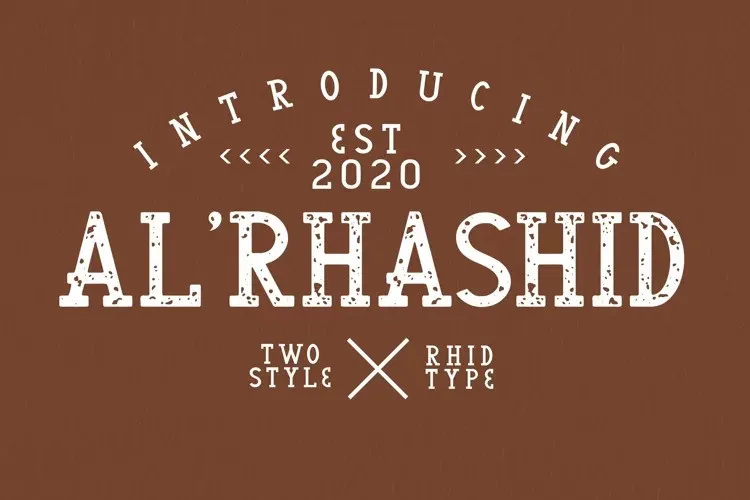
A Al’Rhasid Font é uma seleção do seu portfólio para quem busca tradição e simplicidade em cada letra. Inspirada no estilo das antigas impressões em signa, essa slab serif apresenta um charme quase antigo, com traços grossos que remetem à sensação de trabalho manual na indústria da gráfica dos anos passados. Suas letras são finas e delicadas, sem perdas nos detalhes, proporcionando uma aparência vibrante e moderna em qualquer design que você criar. A Al’Rhasid é a escolha ideal para aqueles buscando um toque clássico em seus trabalhos gráficos, garantindo um resultado único e de alta qualidade. Como cada design deve ser único, essa fonte traz um toque especial às suas criações, oferecendo-lhe uma ferramenta poderosa para expressar-se de forma ainda mais profunda e criativa no universo da impressão digital. Confie nela sem medo em seus projetos, e você não terá nenhum motivo para se arrepender.